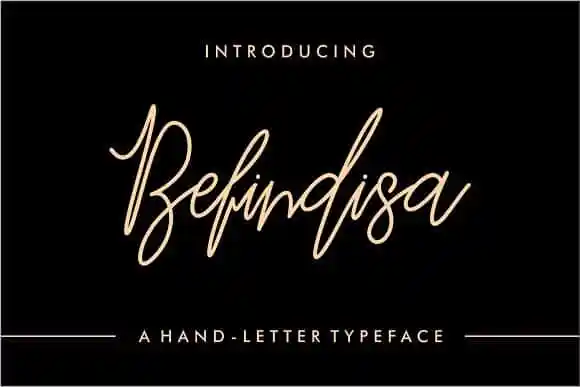
Befindisa Script Font – Download Grátis
Befindisa Script é uma fonte script ideal para quem busca um toque elegante e sofisticado em suas criações. Esta fonte foi criada pelo designer 178-MC, seguindo a linha de calligrafia refinada da Mercurial. Com Befindisa Script você pode transformar qualquer texto em uma verdadeira obra de arte com sua facilidade de escrita e sua capacidade única de criar um estilo próprio. A particularidade deste tipo de fonte é que cada letra foi cuidadosamente personalizada para garantir que seus textos sempre soem elegantes e sofisticados. Este design exibido em calligrafia pode ser perfeitamente aplicado a uma variedade de formatos como cartazes, convites, mensagens pessoais, rótulos ou até mesmo embalagens de moda e acessórios. Befindisa Script é perfeito para aqueles que querem adicionar um toque único e sofisticado a seus projetos visuais, seja em design gráfico, arte digital ou aplicação em produtos físicos. Com uma fonte desta qualidade, você pode aproveitar ao máximo os possíveis e limites da Befindisa Script, criando mensagens memoráveis para qualquer tipo de projeto. Através dela, sua comunicação visual se torna mais forte e atraente, capturando a atenção do público com facilidade. E, não é à toa que ela é recomendada tanto para uso em cartazes quanto para as mais delicadas mensagens pessoais.